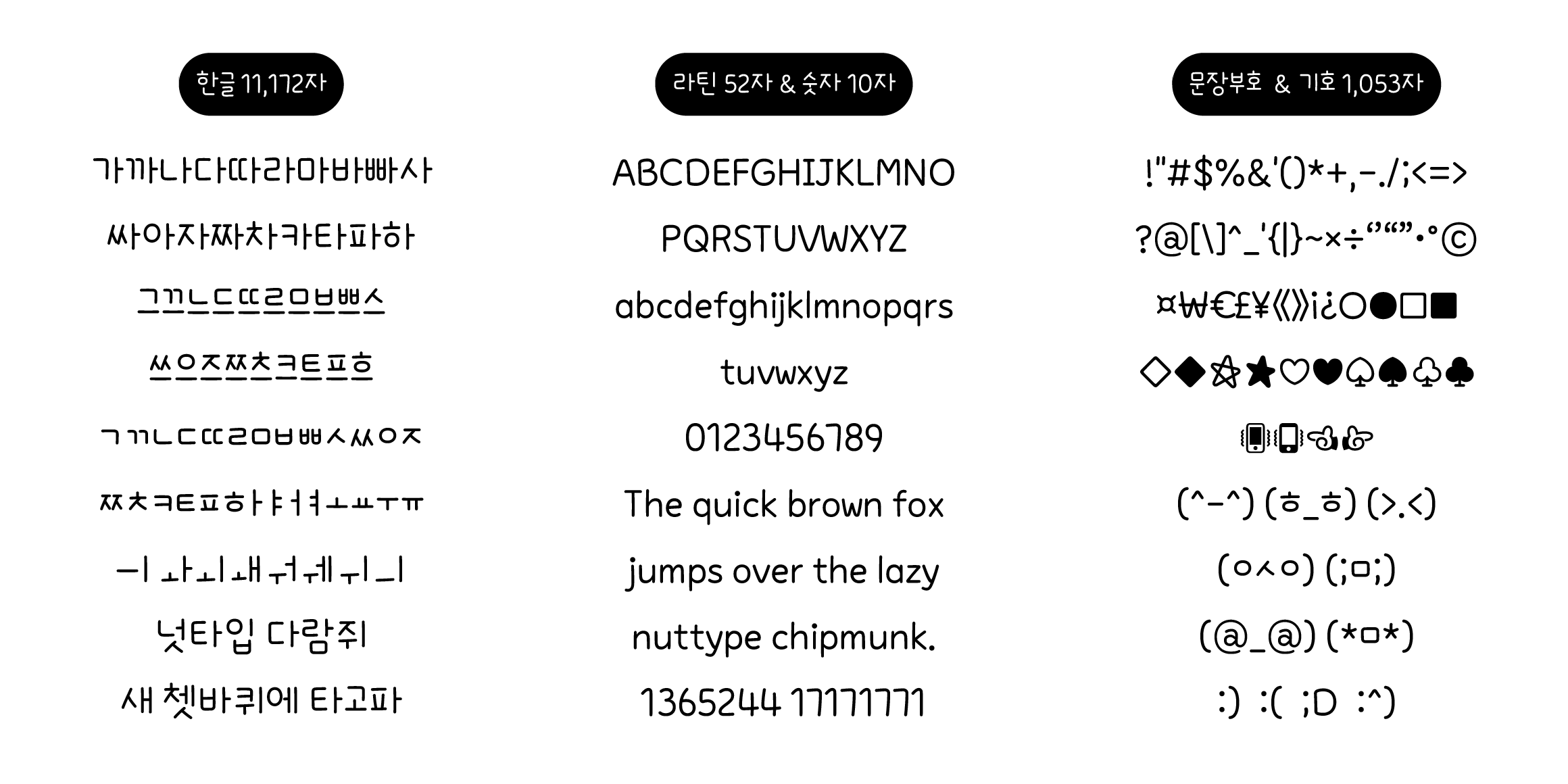
unu아이스하면카푸치노
unu
unu아이스하면카푸치노 font in use
이 서체는 시원스런 세로줄기와 오밀조밀한 자소들의 생김새가 사랑스러운 손글씨입니다. 사랑하는 누군가에게 따뜻한 마음을 전하고 싶을때, 내 소중한 다이어리에 오늘을 기록하고 싶을때 추천드립니다. 유앤유서체는 당신의 따뜻한 마음을 전해드립니다.(컬러가 적용되지 않는 기기나 앱이 있을 수 있으며, 두껍게(Bold)처리시 두께 변화가 없을 수 있습니다.)
• 김영아
• unu아이스하면카푸치노 / unuicecappuccino